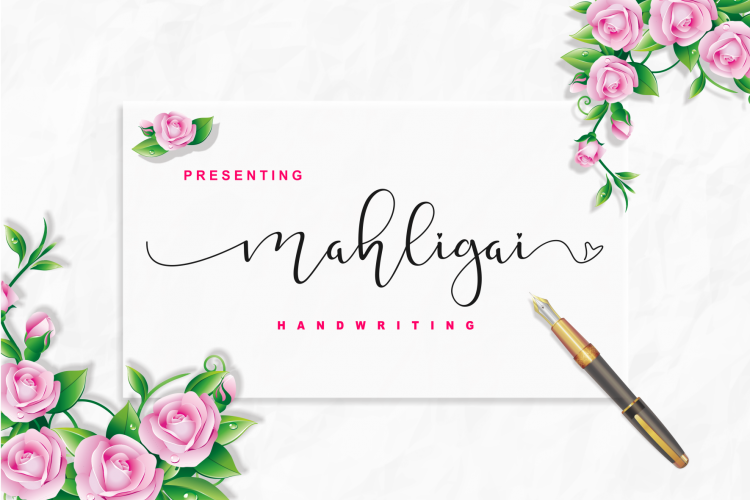
Mahligai Calligraphy Font – Download Grátis
A Mahligai Calligraphy Font é uma elegante novidade na categoria dos caracteres script. Desenvolvida por Malindo Creative, essa fonte é perfeita para quem deseja fazer declarações estilosas ou adicionar um toque de classe a seus projetos gráficos. Este tipo de escrita possui traços irregulares entre o alto e o baixo, com uma aparência suave e grossa, que permite adaptação a diversos formatos de design e impressão. Esta fonte é perfeita para diversas aplicações, como banners, folders, convites, camisetas, chinelos, calendários, panfletos e muito mais. Suportando várias línguas, Mahligai Calligraphy Font faz parte do armário de qualquer designer. Seja você um profissional ou iniciante, essa fonte pode ajudá-lo a criar projetos de design incríveis. Através da Mahligai, os designers podem expressar sua criatividade com um toque de elegância e sofisticação.